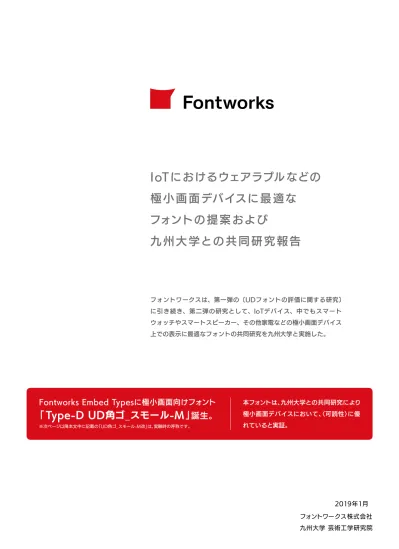
実 験 概 要
研究員
コンテンツクリエーティブデザイン部門
⃝
伊原 久裕 教授
⃝
藤 紀里子 助教
⃝
楊 寧 学術研究員
デザイン人間科学部門
⃝
須長 正治 准教授
研究名
デバイス表示の特性に基づいたUDフォントの
デザイン性に関する研究
研究概要
フォントの主観評価実験およびフォント形態属性の計測を
行い、得られたデータの解析・比較を行うことで、心理
的側面と物理的側面の両面から総合的な分析を行うこと
実験の流れ
今回の実験では、3回の予備実験にて、本実験の実験用
フォントを選出。
起点となるフォントの選出方法については、フォントワー
クスが以前九州大学と行った共同研究〔UDフォントの評
フォントワークスは、九州大学と[デバイス表示の特性に基づいたUDフォント
のデザイン性に関する研究]を共同研究として実施。共同研究内で、IoTにおけ
るウェアラブルなどの極小画面デバイスに最適なフォントの実験を、九州大学
芸術工学研究院のコンテンツ・クリエーティブデザイン部門およびデザイン人間
科学部門の下記教員との共同研究の一環として行った。
UD角ゴ_スモール-Rと
UD角ゴ_スモール-Mの
中間の太さのフォント
UD角ゴ_スモール-RMを
94‒96%縮小したフォント
UD丸ゴ_スモール-Mと
UD丸ゴ_スモール-Dの中間の太さ
筑紫A丸ゴシック-Mと
筑紫A丸ゴシック-Dの中間の太さ
実 験 に つ い て
今回の実験で比較対象とした
フォントワークスフォント
※下線のフォントは今回の実験を行うにあたり、予備実験時の結果を踏まえ
既存のフォントを改良。
価に関する研究〕の結果を踏まえ、すでに可読性の高さ
が実証されている、フォントワークスのユニバーサルデ
ザイン(UD)フォント
(備考:※1)
の角ゴシック体にし、中
でも、より字面の大きいラージタイプを選択。UD角ゴ_
ラージを起点フォントとして選出。
また、他社製UDフォントも比較対象として選択。
(予備実験の詳細は2ページ)
予 備 実 験
予備実験については、前回の九州大学とのUDフォントにおける研究で可読性に優れていると結果が出た
「UD角ゴ_ラージ」を起点に、本実験のフォントの選定を行うために実施。以下のフォントの組み合わせで3つの予備実験を行った。
極小画面に、よりたくさんの文字を表示できるよう、コンデンス(長体)書体を含め、再度実験。
コンデンス(長体)書体は良い結果が出なかったため、候補から除外した。
また、被験者が、可読性を評価する際に、字面の大きさや濃度(黒み)などの、形態属性か
ら影響を受けることがわかっており、より小さな字面の方が、濃度(黒み)が増し評価が高
くなるのではないかと推測し、当初は、字面の大きなラージタイプでの実験だったが「UD
角ゴ_スモール」や「筑紫ゴシック」などの字面の小さなフォントを追加して再度実験。
実 験 結 果
3回の予備実験の結果、極小画面デバイスへの文字
表示の条件に対して、被験者は、字面の大きさや
濃度(黒み)など、いくつかの形態属性(備考:※2)
か
ら評価を行う傾向が見られた。よって起点となる
「UD角ゴ_ラージ」よりも字面が小さく、濃度(黒
み)が強い「UD角ゴ_スモール」を投入。
被験者のインタビューでは、コンデンスフォント
に対して、長体率90%のフォントが長体率80%の
フォントより読みやすいと評価されている。また、
丸ゴシック体については、文字の表示サイズが小さ
いので、角ゴシック体と明確に区別することはでき
ないとのことだった。
以上の結果を踏まえ、実験フォントを角ゴシック体
に限定して、フォントワークス社製UDフォントと
他社UDフォントから、実験フォントを選定した。
1. UD角ゴ_ラージ-R
2. 他社UDフォントⒶ(可読性1位)
3. 他社UDフォントⒷ(可読性2位)
4. 他社UDフォントⒺ(可読性1位)
1. UD角ゴ_ラージ-R
2. UD角ゴ_スモール-RM※1
3. 筑紫ゴシック-D
4. ニューセザンヌ-M
5. 筑紫A丸ゴシック-MD※2
6. UD丸ゴ_スモール-MD※3
1. UD角ゴ_ラージ-R
2. 他社UDフォントⒶ(可読性1位)
3. 他社UDフォントⒷ(可読性2位)
4. UD角ゴ_コンデンス80-R/
他社UDフォントⒶコンデンス90
フォントワークス社製UDフォント
+ 他社UDフォント(可読性実験の成績の良いフォント)
フォントワークス社製UDフォント
+ 他社UDフォント(可読性実験の成績の良いフォント)
+ コンデンスフォント(フォントワークス社と他社)
フォントワークス社製UDフォント
+ フォントワークス社製他フォント(丸ゴシック体も含めて)
実験環境
実験画面
実験方法
実験装置 コンピュータ制御のiPad mini 4
観察距離 30cm(目と平行)
観察条件 暗室
背景色および文字色 黒(<0.35cd/㎡)/白(<185cd/㎡)
見出し 文字種混合の2行の短文、プログラム上の設定上は16ptのサイズ
本文(大) 文字種混合の7行の連続文、プログラム上の設定上は14ptのサイズ
本文(小) 文字種混合の7行の連続文、プログラム上の設定上は11ptのサイズ
提示方法 一対の文字列提示
評価方法 一対比較法(二つのサンプルを比較し勝敗を決定)
被験者の課題 提示された文字列対に対して、どちらが「読みやすいか」を回答
2行短文
(16pt):見出し
7行連続文
(14pt):本文
(大)
7行連続文
(11pt):本文
(小)
※1:UD角ゴ_スモール-RとUD角ゴ_スモール-Mの中間の太さのフォント
※2:筑紫A丸ゴシック-Mと筑紫A丸ゴシック-Dの中間の太さのフォント
※3:UD角ゴ_スモール-MとUD角ゴ_スモール-Dの中間の太さのフォント
※画像は実際の実験で使用されたものではなく、イメージです。
本 実 験 1- A
可 読 性 実 験[ 概 要 ]
実験装置 コンピュータ制御のiPad mini 4
観察距離 30cm(目と平行)
観察条件 暗室
被験者 若年者(40名)
背景色
および文字色 黒(<0.35 cd/㎡)白(<185 cd/㎡)
見出し プログラム上の設定上は21ptのサイズ文字種混合の2行の短文、
本文(大) プログラム上の設定上は18ptのサイズ文字種混合の7行の連続文、
本文(小) プログラム上の設定上は16ptのサイズ文字種混合の8行の連続文、
提示方法 一対の文字列提示
評価方法 (二つのサンプルを比較し勝敗を決定)一対比較法
被験者の課題 どちらが「読みやすいか」を回答提示された文字列対に対して、
・筑紫ゴシック-D
・UD角ゴ_スモール-RM(P1参照)
・UD角ゴ_SS-RM(P1参照)
・他社UDフォントⒶ
・他社UDフォントⒷ
・他社UDフォントⒸ
・他社フォントⒹ
実験環境
実験方法
実験フォント
(7書体)
2行短文
(21pt)
:見出し
1
7行連続文
(18pt)
:本文
(大)
2
8行連続文
(16pt)
:本文
(小)
3
実験内容と評価方法について
験結果に影響を与えている可能性があると考える。下図は本文(大)白背景の相関図。可読性の高
い順に左からフォントを並べ、その濃度を折れ線グラフで示している。折れ線グラフは右肩下がり
の傾向を示しているため、濃度が高いフォントの方が、可読性が高くなるのではないかという推測
を行う。
可読性
濃度(平均)
左から順に
・他社UDフォントⒶ
・他社UDフォントⒸ
・UD角ゴ_スモール-RM
・UD角ゴ_SS-RM
・他社UDフォントⒷ
・他社フォントⒹ
・筑紫ゴシック-D